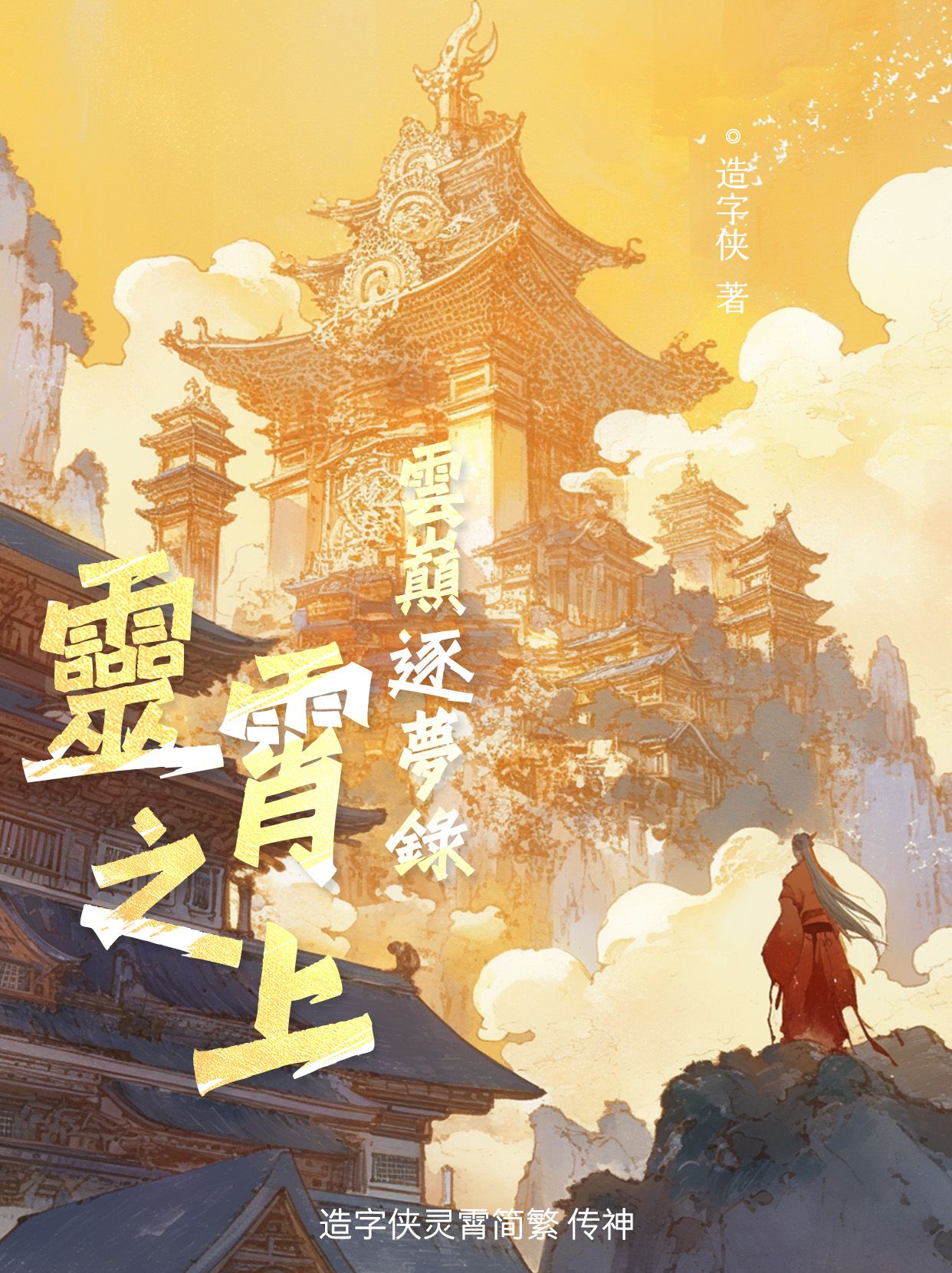
四款动漫设计专属字体推荐:以笔触唤醒次元生命力
在动漫视觉语言中,字体不仅是信息载体,更是世界观构建的基石。本文精选四款风格迥异的商业字体,从仙侠玄幻到青春幻想,为不同题材的动漫设计提供精准的视觉解决方案。
一、造字侠灵霄简繁 传神
以《西游记》灵霄宝殿为灵感,这款硬笔手写字将“剑气”融入笔画。其字形如利剑出鞘,笔画刚劲挺拔,转折处暗藏锋芒,尤其适合仙侠、玄幻题材的标题设计。例如,在国风网游《九霄御剑录》海报中,该字体以烫金效果呈现,与云纹背景相映成趣,瞬间传递出“一剑破苍穹”的磅礴气势。其简繁双版本支持多语言排版,满足全球化发行需求。
二、字恋狂白日梦简
这款字体以“凌乱”为美学核心,笔画如梦境碎片般交织,在失控中暗藏秩序。其不规则的倾斜角度与虚实相生的笔触,完美适配青春漫画、奇幻绘本的场景。例如,在校园奇幻漫画《星屑物语》中,角色内心独白以该字体呈现,搭配水彩晕染背景,营造出“现实与幻想交织”的朦胧感。设计师可利用其动态笔触,强化角色情绪的视觉张力。
三、字恋狂漫野絮风
以“絮风”为名的直线字体,通过去钩处理与笔画断开设计,在规整中制造呼吸感。其字型大小错落有致,灰度均匀,适用于对话气泡、章节标题等场景。例如,在冒险题材动画《荒野拾遗者》中,角色台词以絮风体搭配做旧纸张纹理,既保留手写温度,又通过大小对比增强阅读节奏。该字体尤其适合需要兼顾信息传达与艺术感的分镜设计。
四、高手兵克战甲体
这款创意字体以“战甲”为视觉符号,粗壮笔画如金属铠甲般厚重,折角处锐利如刃。其强烈的视觉冲击力,使其成为科幻、机甲题材的视觉锚点。例如,在机甲格斗游戏《重装核心》的LOGO设计中,战甲体与金属渐变、铆钉元素结合,瞬间传递出“重装上阵”的压迫感。设计师可通过调整字体描边与立体效果,进一步强化机械质感。
从仙侠世界的凌厉剑气到机甲宇宙的金属轰鸣,这四款字体以差异化风格构建出多维度的动漫视觉宇宙。它们不仅是工具,更是故事叙事的延伸。设计师可根据题材调性自由组合,让字体成为动漫世界的“第二语言”。